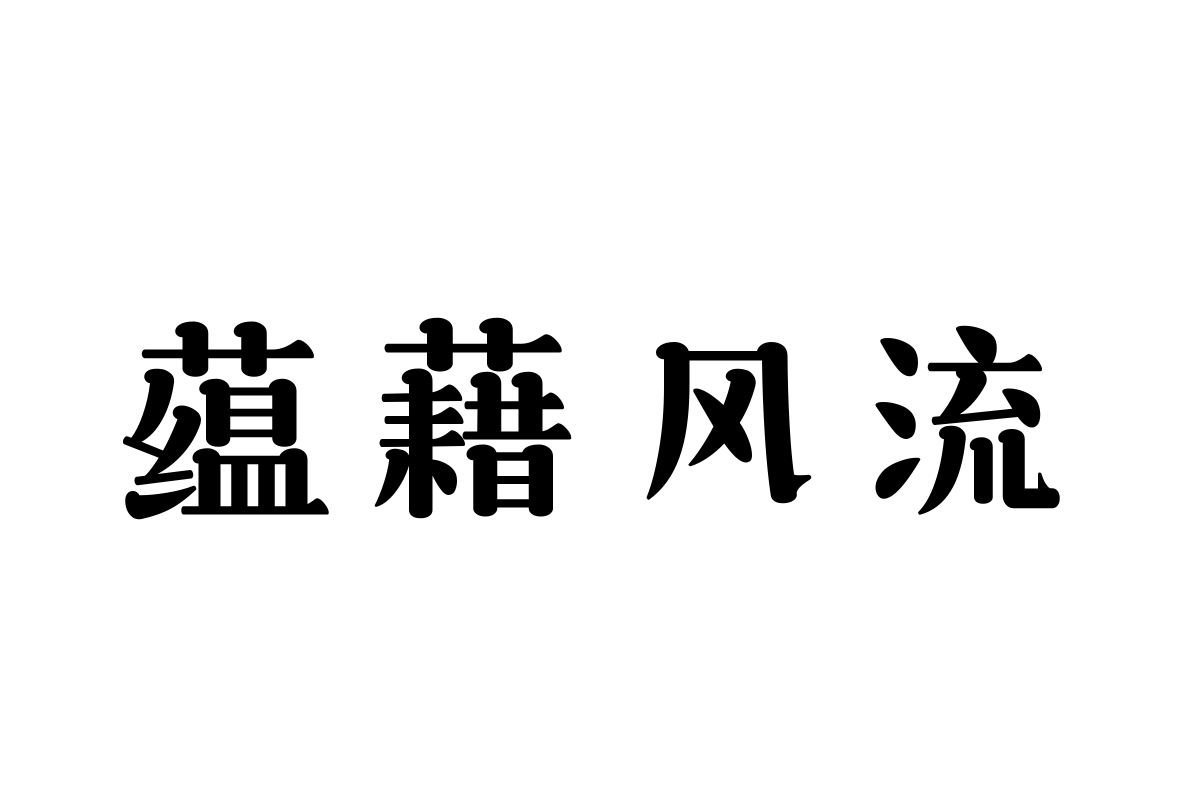
三极悠闲宋简体是专为中文排版设计的字体,具有以下特点:
1. 字形优美:三极悠闲宋简体采用了传统的宋体风格,字形规整、清晰,易于阅读。
2. 笔画流畅:该字体的笔画粗细适中,线条流畅,给人一种舒适的感觉。
3. 结构紧凑:三极悠闲宋简体的字形结构紧凑,有利于节省空间,适合在各种尺寸的文本中使用。
5. 可定制性强:该字体提供了丰富的字重和行距设置选项,用户可以根据自己的需求进行个性化设置。
6. 适用范围广:三极悠闲宋简体适用于各种类型的文本,如报纸、杂志、书籍、广告等。